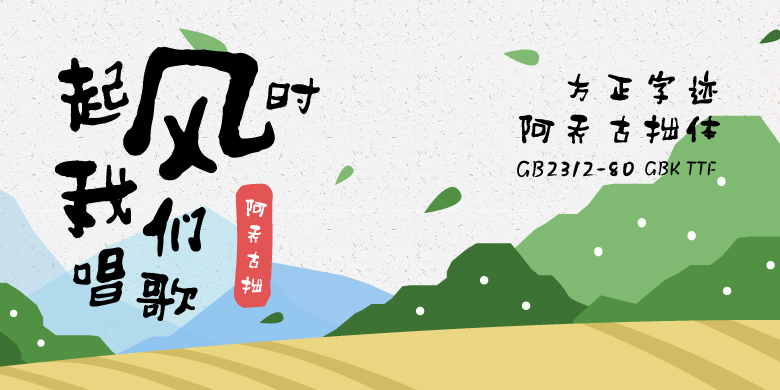
方正字迹-阿乔古拙体
字体品牌: 方正字迹 设计师:赵金桥 字体分类:创意书写 字体属性:精品字 字符集:大陆简体(GB2312-80)、简繁扩展(GBK) 发布时间: 2018
大理阿乔,又名阿乔,作者原名赵金桥,移居大理,喜欢书法,书风活泼有趣,拙中有巧,好游走,心顽童,温和善良,有些装逼,但不过分,内心坚信写字乃修心,随性的写,随性的活。阿乔古拙体,是承传了中国古代书法的大法度之下又融入了当今审美和自我个性风格的一种字体,一笔一划随性稚趣,拙中有巧,活泼,耐看。适合广告,牌匾,标题,书籍装帧等,具有传统中的新生儿的气质,是年轻人喜欢的一种字体。